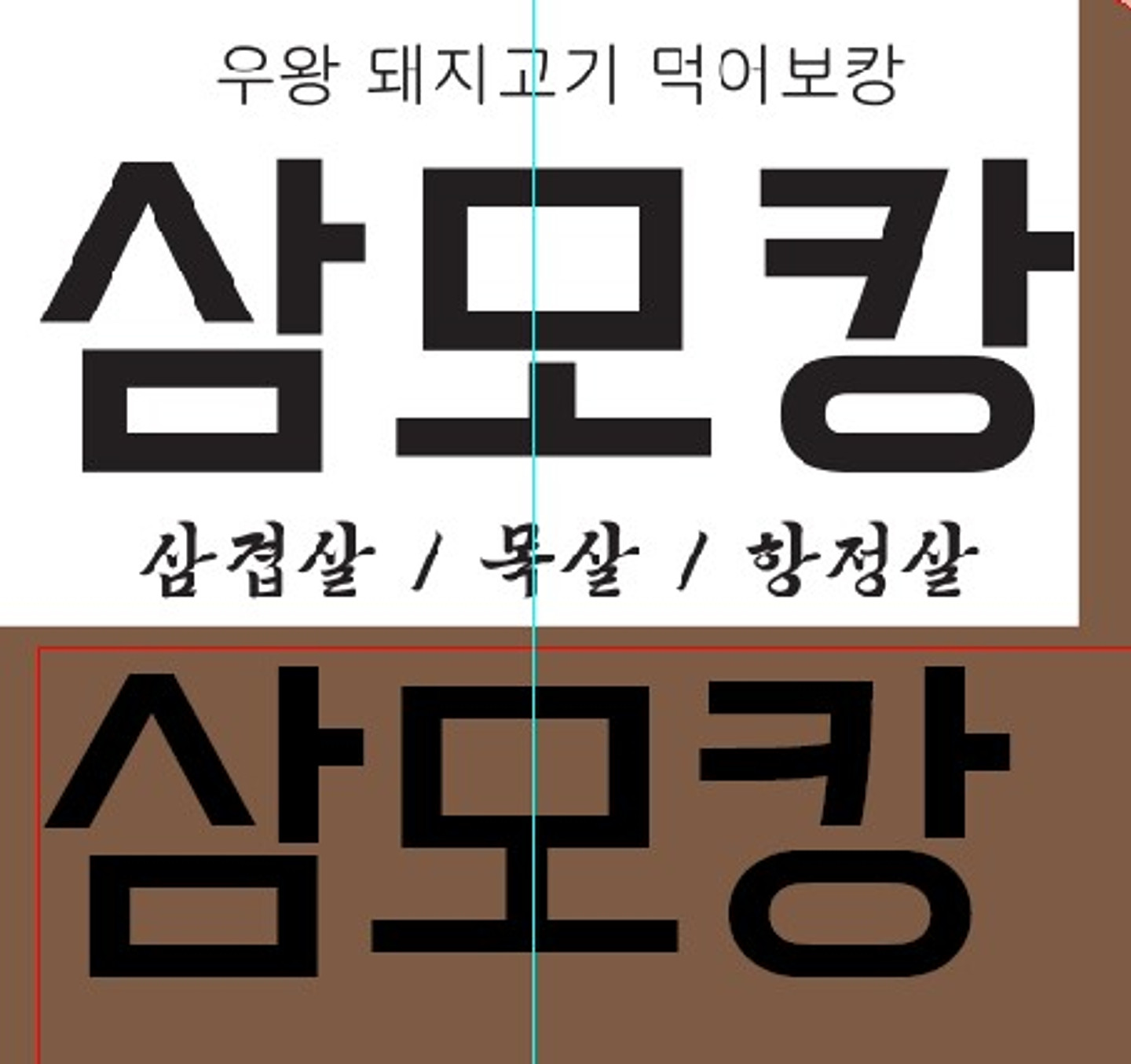
위에 하얀배경 폰트 알 수 있을요? 갈색배경은 제가 적어둔건데 삼 만보면 평창체 볼드인데 모캉을 보면 아니거든요..? ㅠㅠ 폰트 알고 싶어요! 그리고 하얀배경에 "우왕 돼지고기 먹어보캉" "삼겹살/목살/항정살" 이것도 알고 싶어요! 알려주시면 감사하겠습니다 ㅠㅠ
210 평화
삼겹살~ 폰트입니당
HU네모굴림
우왕~ 폰트 같아용